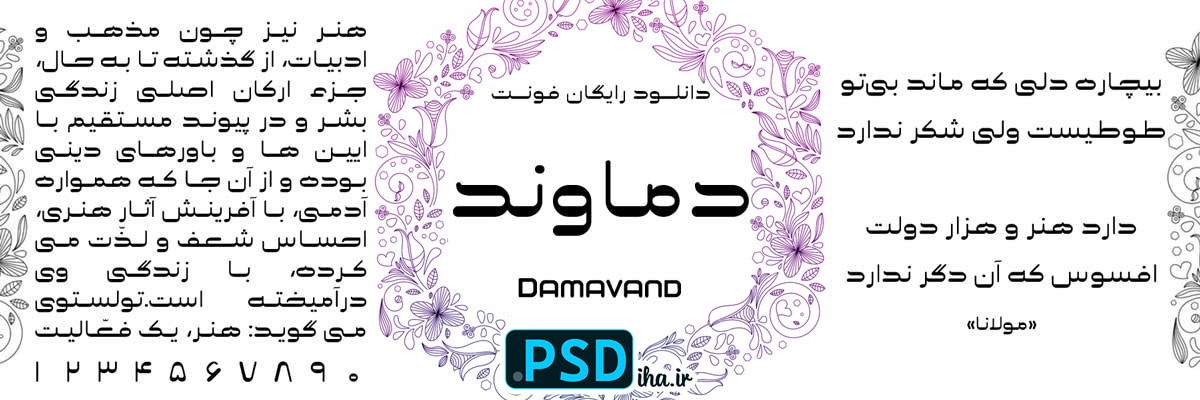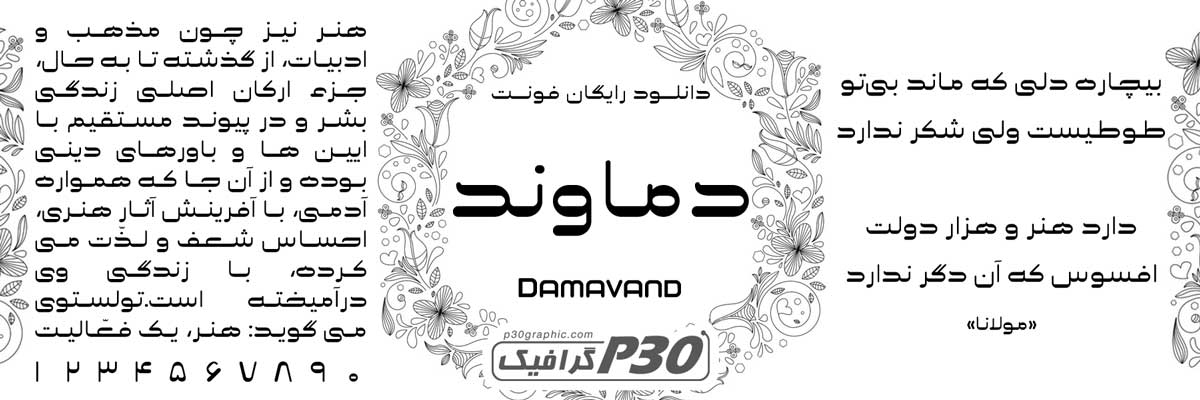
دانلود فونت دماوند
فونت دماوند
فونت دماوند یکی از محبوب‌ترین فونت‌های فارسی است که با طراحی منحصربه‌فرد و کشیده، زیبایی و قدرت طبیعت ایران را به پروژه‌های گرافیکی شما می‌آورد. اگر به دنبال دانلود رایگان فونت دماوند رایگان با کیفیت بالا هستید، وب‌سایت پی اس دی ها (PSDiha.ir) بهترین منبع برای طراحان، گرافیست‌ها و علاقه‌مندان به تایپوگرافی فارسی است.
• مناسب برای پروژه‌های حرفه‌ای: لوگو، پوستر، بنر تبلیغاتی، بسته‌بندی، طراحی وب‌سایت و حتی موشن‌گرافیک.
• حروفچینی دقیق فارسی: پشتیبانی کامل از کرنینگ، لیگچرها و علائم نگارشی فارسی برای خروجی بی‌نقص.
ویژگی‌های کلیدی فونت دماوند:
• سبک: Sans-Serif با لبه‌های نرم و مدرن
• وزن‌ها: Regular, Bold, Light (در نسخه کامل)
• زبان‌ها: فارسی، عربی، لاتین
• کاربرد: چاپ، دیجیتال، برندینگ